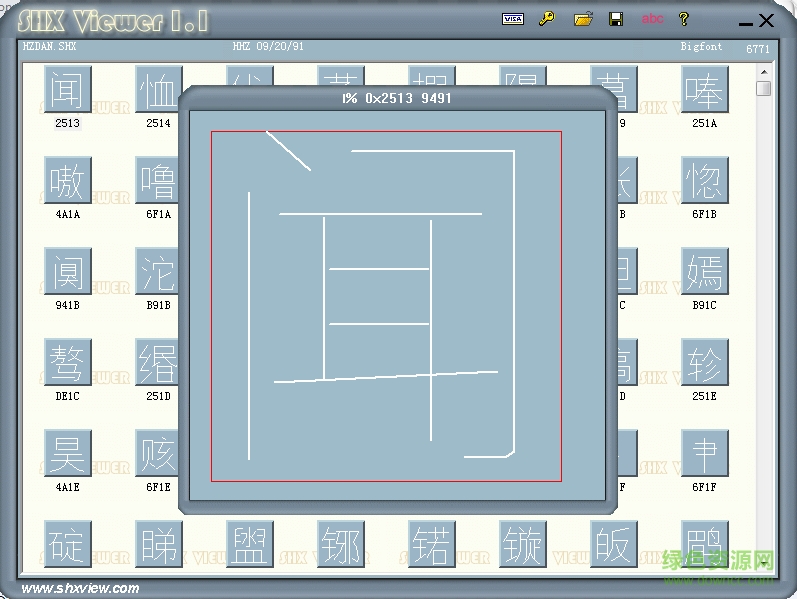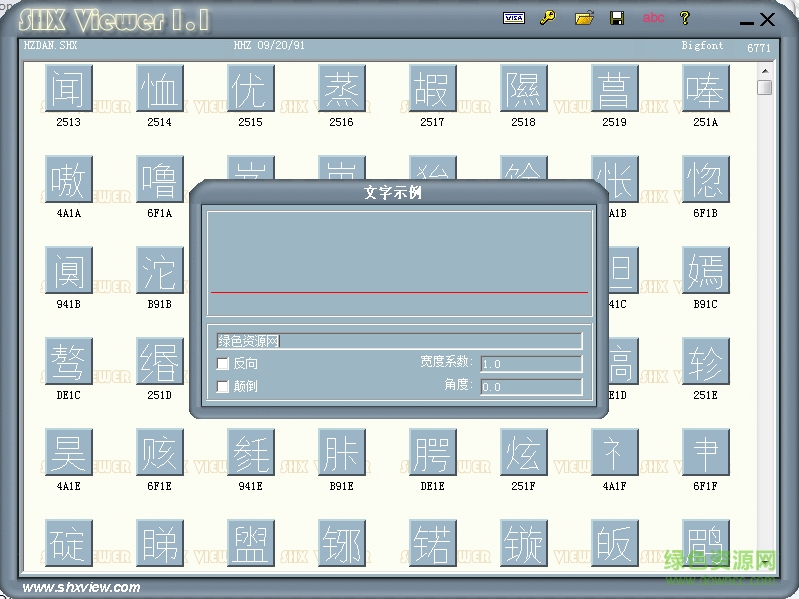
hzdan.shx是一款拥有6771个字的cad字体,归属于大字体系列,支持部分繁体字输入,字迹精简如镌刻,给人纯净清秀的阅读观感,绿色资源网诚意推荐!
1、在dwg文件的存储上占用的空间小,在显示的速度上比较快。特别是文字比较多的情况下,regen的重显的速度上的差异更明显,在实时移动(pan)的更新上不存在时差现象。
2、由于windows字体为外来字体(相对于shx字体),在生成及编辑的过程中,还不能做到完美无缺。比如,truetype字体(windows字体)的文字在移动、拷贝的过程中,句子的长度可能与实际的长度不同,影响了参考定位。再如,truetype字体的实际高度可能与指定的高度之间有差异,不能精确地指定字高,只能通过试错的方式确定,影响了绘图的速度,也影响了编程控制的难度。 3、由于shx字体为线型字体,可以像线段一样指定特别属性,产生特殊效果。比如,可以指定厚度值,从而产生立体效果。
4、与truetype字体相比,shx字体美观效果不够理想,但在工程中尚可满足需要。shx字体相当于硬笔书法,在模拟毛笔书法上存有差距。